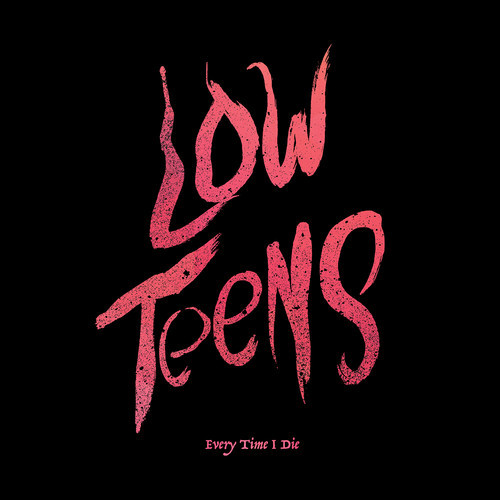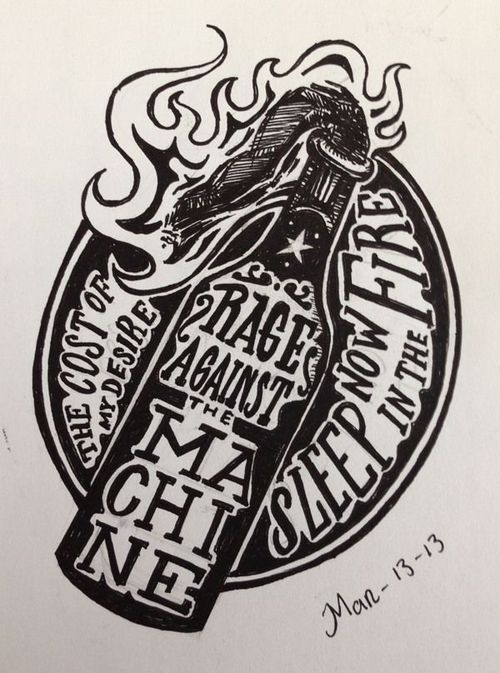
в чем разница и почему важно ее понимать?
Хотя указанные термины зачастую используются как синонимы, между гарнитурой и шрифтом есть различия. Поскольку они не слишком значительны, может иногда возникать путаница.
Гарнитуры и шрифты всегда были и остаются важной частью брендинга. Чтобы четко сформулировать, каким должен быть дизайн, вам необходимо понять как историческое значение этих терминов, так и их современную интерпретацию. В статье мы рассмотрим эти понятия, а также различия между ними, чтобы вы могли эффективно и профессионально их использовать.
Гарнитура vs. шрифт — в чем различия?
Если гарнитура (typeface) — это набор конструктивных особенностей букв или других символов, то шрифт (font) — это совокупность символов внутри гарнитуры, отличающихся начертанием и размером. При этом семейством (font family) называют группу связанных между собой шрифтов.
Эти определения могут показаться запутанными, поэтому рассмотрим, что означает каждый термин подробнее.
Что такое гарнитура?
Гарнитура — это совокупность конструктивных особенностей букв и других символов, например, наличие или отсутствие засечек, начертание и баланс букв, интервалы и соотношение высоты прописных и строчных букв.
В зависимости от стиля можно выделить несколько категорий гарнитур. Самые распространенные из них:
С засечками
Такие гарнитуры, как следует из названия, включают шрифты с засечками. Эти шрифты обычно воспринимаются как изысканные и классические.
Изображение Post Press.К примеру, Garamond — популярная гарнитура шрифта с засечками.
Bodoni и Didot — еще две популярные гарнитуры указанного типа.
Многие шрифты с засечками появились сотни лет назад и имеют богатую историю. Один из старейших шрифтов западного мира, Roman, был создан Николасом Йенсеном в 1470 году для того, чтобы сделать печатный текст более читабельным, поскольку до этого момента в европейских книгах использовался шрифт Blackletter, напоминающий рукописный текст.
Шрифт Blackletter, созданный на основе каллиграфии, которая применялась для копирования книг вручную в средние века. Изображение Toptal.com.
Без засечек
В отличие от шрифтов с засечками, у входящих в такие гарнитуры шрифтов они отсутствуют. Их можно охарактеризовать как непринужденные и неформальные.
Helvetica — известный шрифт без засечек, как Verdana и Futura.
Декоративные
Декоративные гарнитуры включают забавные, привлекающие внимание шрифты, которые в отличие от стандартных шрифтов с засечками и без имеют ограниченную сферу применения.
Например, известные декоративные шрифты: Outlaw и Morris.
Outlaw, FFonts.net
Эти шрифты не используются для основного текста не только потому, что они могут отвлекать пользователя, но и по той причине, что такой текст трудно читать, особенно, если шрифт маленького размера.
Хотя декоративный шрифт может отлично привлекать внимание к заголовку или наружной вывеске, он способен отпугнуть клиентов, если используется в меню или брошюре.
Рукописные
Такие гарнитуры включают шрифты, которые выглядят как написанный от руки текст. Если вы хотите показать, что предлагаете сделанные вручную, персонализированные продукты, рукописный шрифт может стать отличным выбором для вашего бренда.
Рукописные шрифты могут быть как простыми, так и витиеватыми. Среди популярных можно назвать: Kuenstler Script, Kauffmann and Brush Script.
Как и декоративные шрифты, рукописные затрудняют чтение, особенно если имеют маленькие размеры. Используйте их лишь в логотипах, заголовках или на вывесках, а шрифты с засечками и без засечек подойдут для больших фрагментов текста.
Обратите внимание, как название бренда выделено с помощью рукописного шрифта, в то время, как в оставшейся части логотипа использован простой шрифт без засечек.
Логотип разработан : : scott : :.
Что такое шрифт?
Шрифт — это набор символов определенного начертания или размера, входящий в состав гарнитуры. Таким образом, обычные, жирные, курсивные либо узкие элементы гарнитуры определенного размера составляют то, что называется шрифтом.
Вот простой способ понять, чем различаются гарнитуры и шрифты. Откройте Google Docs и нажмите на раскрывающееся меню шрифтов. Справа от некоторых опций есть маленькая стрелка. Наведите курсор мыши на нее и вы увидите разные варианты, например “тонкий”, “полужирный”, “жирный”.
В этом случае главные опции — это гарнитуры, а варианты под стрелочкой — шрифты.
Встречайте семейство шрифтов
Семейство — это группа связанных между собой шрифтов. Garamond — это гарнитура, характеризующаяся набором конструктивных особенностей букв и других символов. В эту гарнитуру входит множество шрифтов. Например, курсив или полужирный шрифт или шрифт размером 14 или 16pt.
Совокупность всех этих шрифтов и есть семейство.
Гарнитуры и шрифты: очень краткая история
Итак, почему мы вообще разграничиваем шрифты и гарнитуры?
Следует обратиться к тем временам, когда для печати текста использовались блочные буквы. Создавались специальные наборы таких букв, отличающиеся уникальным внешним видом, которые получили название “гарнитуры”. Символы определенного типа внутри гарнитуры, например, узкие или полужирные, размещалась в своем отсеке. Именно они и стали основой современных шрифтов.